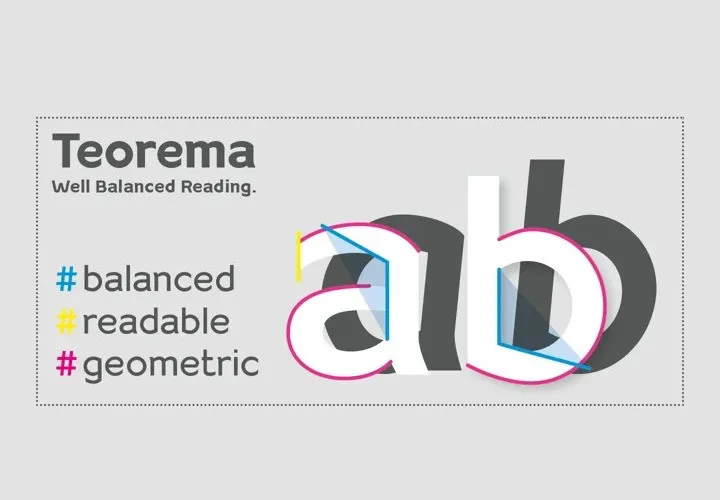
A “Teorema Font” é uma opção elegante para trabalhos visuais que exigem uma aparência clean e moderna. Esta fontes de tipo serifa livre representa a fusão perfeita entre geometria e pragmatismo, com formas geométricas clássicas contrastando com elementos mais afiados em busca do equilíbrio formal para maximizar tanto a reconhecibilidade quanto a legibilidade dos caracteres. Desenvolvida por FSdesign-Salmina, essa fonte é adequada para uso em diversas situações de apresentação ou comunicação visual que requerem um estilo limpo e moderno. Seu design único, centrado nas interações entre formas circulares e afiadas, criou um desafio elegante que resulta na construção de uma identidade visual poderosa e fácil de usar. Ideal para aplicar em materiais digitais ou impressos, a “Teorema Font” é um recurso valioso tanto para profissionais de design quanto para entusiastas. Aqui está o download gratuito da versão regular e bold do caractere reduzido da fonte Teorema.